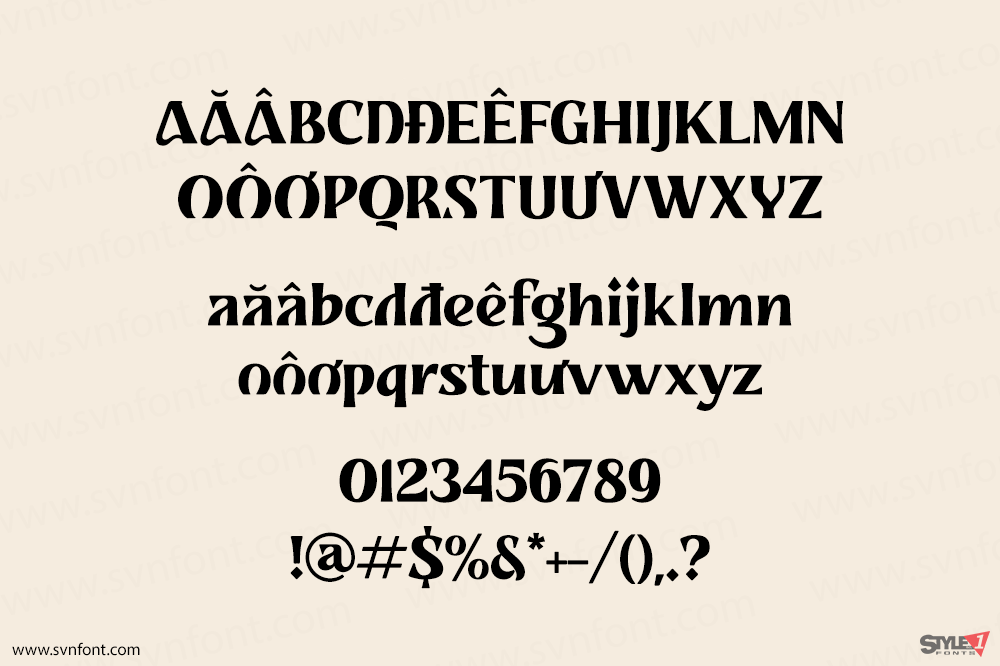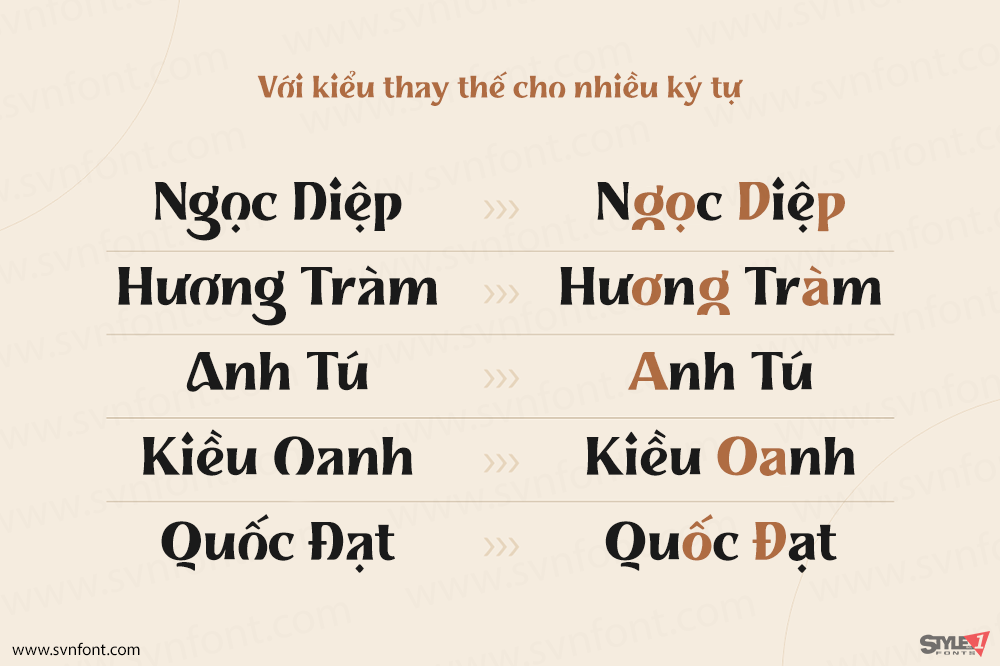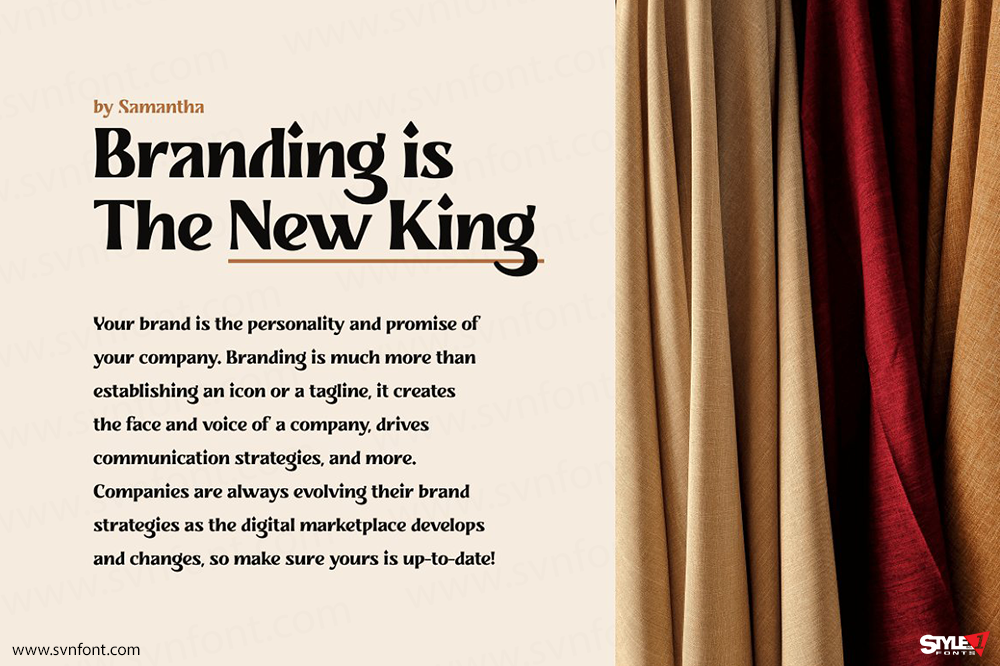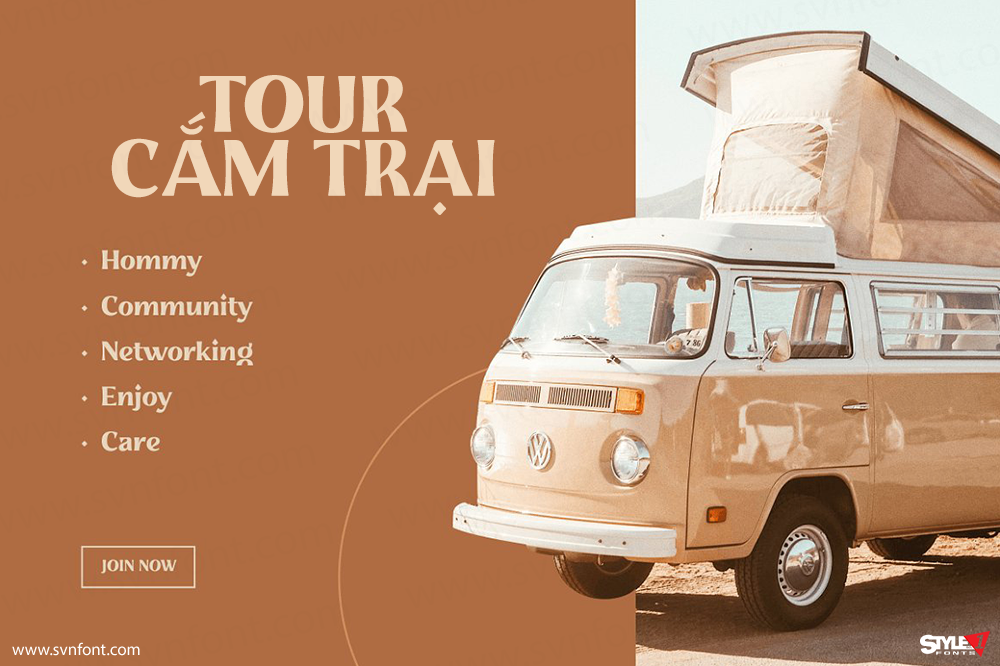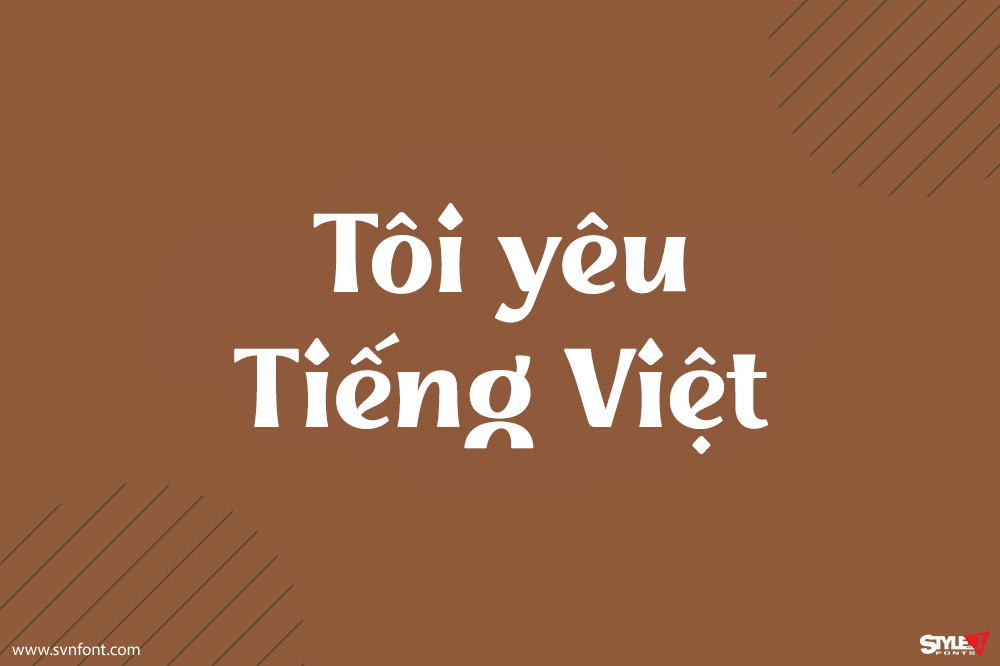
Diamond typeface là một kiểu chữ cũ (old-style), retro, độc đáo và linh hoạt, mang phong cách cổ điển với các ký tự đặc biệt sẵn sàng cho việc xây dựng thương hiệu và tạo sự nổi bật. Đây là một kiểu chữ hiển thị (display typeface) với đường cong độc đáo, hoàn hảo cho các dự án xây dựng thương hiệu, logo, thiết kế đám cưới, bài đăng trên mạng xã hội, quảng cáo, bao bì sản phẩm, thiết kế sản phẩm, nhãn mác, nhiếp ảnh, watermark, thiệp mời, văn phòng phẩm và bất kỳ dự án nào khác, với khả năng dễ đọc cao.